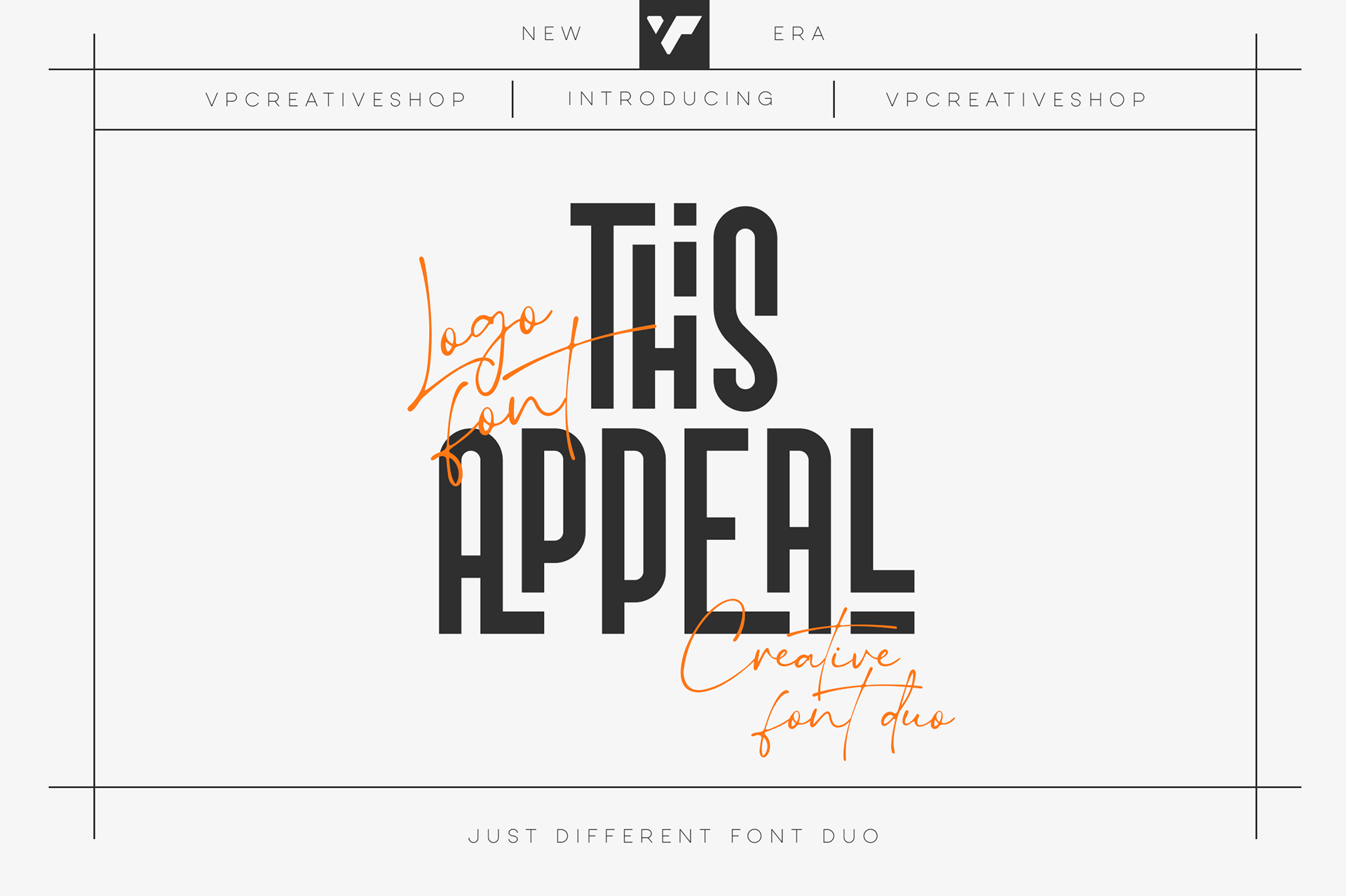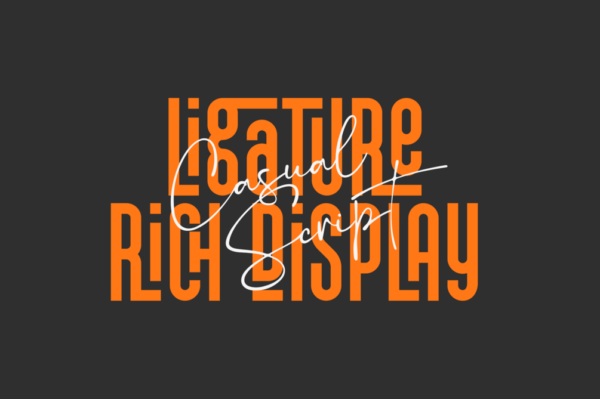
font del giorno: This Appeal
Ti presentiamo “This Appeal”
uno straordinario duo di caratteri che combina brillantemente versatilità e stile. Questo abbinamento unico presenta due caratteri tipografici complementari, ciascuno con il proprio fascino e funzionalità, che lo rendono un must. Con oltre 200 glifi di legatura e ben 70+ glifi alternativi, è la scelta giusta per creare titoli accattivanti e loghi indimenticabili. A complemento di questo c’è un font Brush moderna casual con linee morbide e fluide, per portare un tocco moderno che da un tocco personale e professionale.